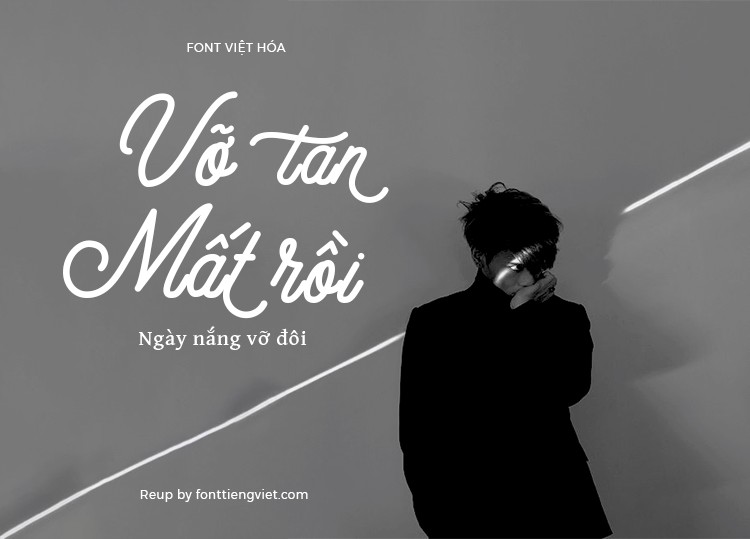
Font việt hóa MTD Himalaya – Nét chữ nghệ thuật độc đáo cho thiết kế sáng tạo
Giới thiệu về Font việt hóa MTD Himalaya
Trong thế giới đồ họa hiện đại, việc tìm kiếm một bộ Font Miễn Phí có phong cách vừa cổ điển vừa tinh tế luôn là ưu tiên hàng đầu của các nhà thiết kế. Font việt hóa MTD Himalaya chính là lựa chọn hoàn hảo dành cho những ai yêu thích vẻ đẹp bay bổng và đầy tính nghệ thuật. Được chuyển ngữ bởi nhóm MTD, bộ font này đã khắc phục hoàn toàn lỗi gõ dấu tiếng Việt, giúp người dùng dễ dàng ứng dụng vào các phần mềm thiết kế chuyên nghiệp như Photoshop, Illustrator hay Canva mà không gặp bất kỳ trở ngại nào về hiển thị.
Đặc điểm nổi bật của Font việt hóa MTD Himalaya
Phong cách thiết kế đặc trưng
Font việt hóa MTD Himalaya sở hữu những đường nét mảnh mai nhưng vẫn giữ được sự cứng cáp cần thiết. Với cấu trúc ký tự thanh thoát, nó mang lại cảm giác nhẹ nhàng tựa như những đỉnh núi tuyết hùng vĩ. Đây là loại phông chữ cực kỳ phù hợp cho các dự án yêu cầu tính thẩm mỹ cao như thiết kế bìa sách, thiệp mời đám cưới hay các poster sự kiện mang hơi hướng vintage. Ngoài ra, sự đa dạng trong các biến thể của bộ font này cũng cho phép bạn linh hoạt sáng tạo nội dung từ tiêu đề lớn đến các đoạn văn bản ngắn trang trí.
Tính ứng dụng cao trong thực tế
Không chỉ dừng lại ở đồ họa quảng cáo, Font việt hóa MTD Himalaya còn được các bạn học sinh và giáo viên ưa chuộng trong việc thiết kế slide bài giảng hoặc làm báo tường điện tử. Nhờ bộ dấu tiếng Việt được trau chuốt tỉ mỉ, các văn bản trở nên chuyên nghiệp và dễ đọc hơn hẳn so với các font mặc định khô khan.
Kết luận về bộ font nghệ thuật này